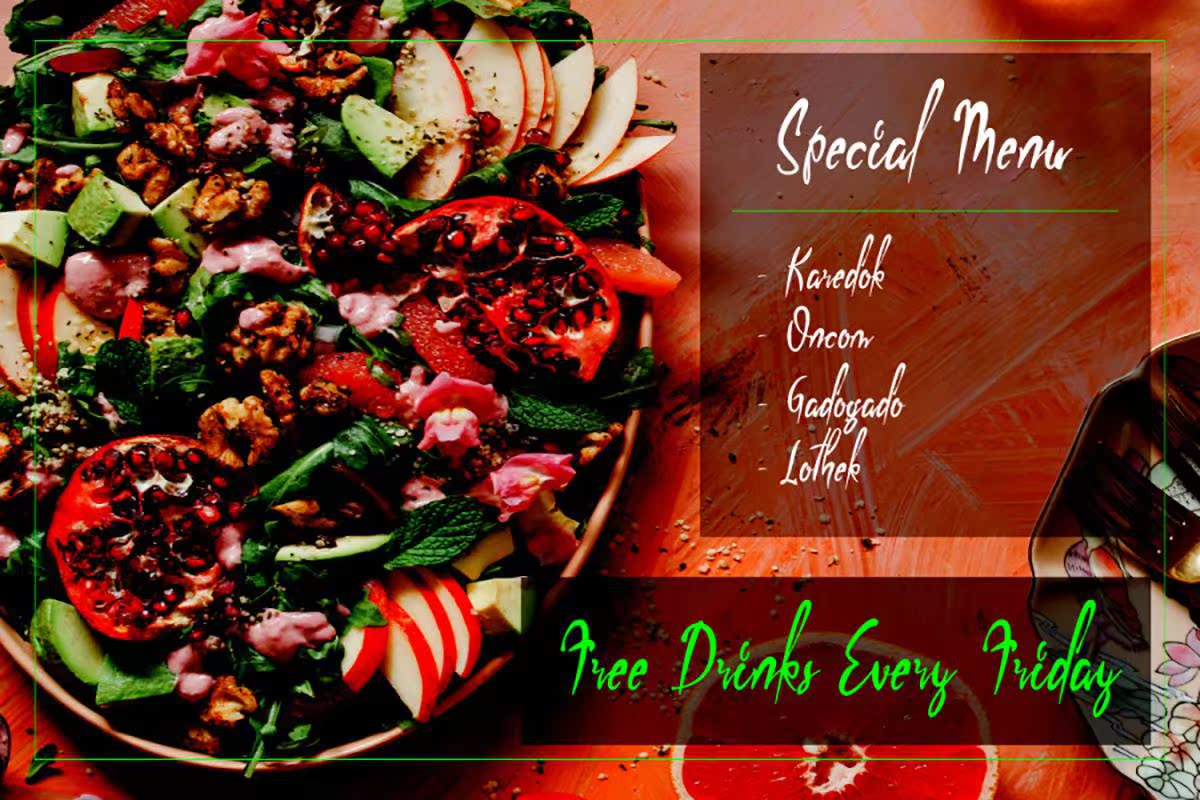
FreeellPacino Handbrush ScriptFont是一种漂亮的粗体ScriptFont。它与一些可以使您的项目成为专业项目的连接符配合使用。FreeellPacino Handbrush ScriptFont也适用于您的工作,如包装、产品、邀请函、名片、品牌等。附带一个可帮助您轻松安装设备的格式文件。此外,此自由方可用于个人许可证。但不要担心,您可以通过购买PremiumVersion获得更多功能。